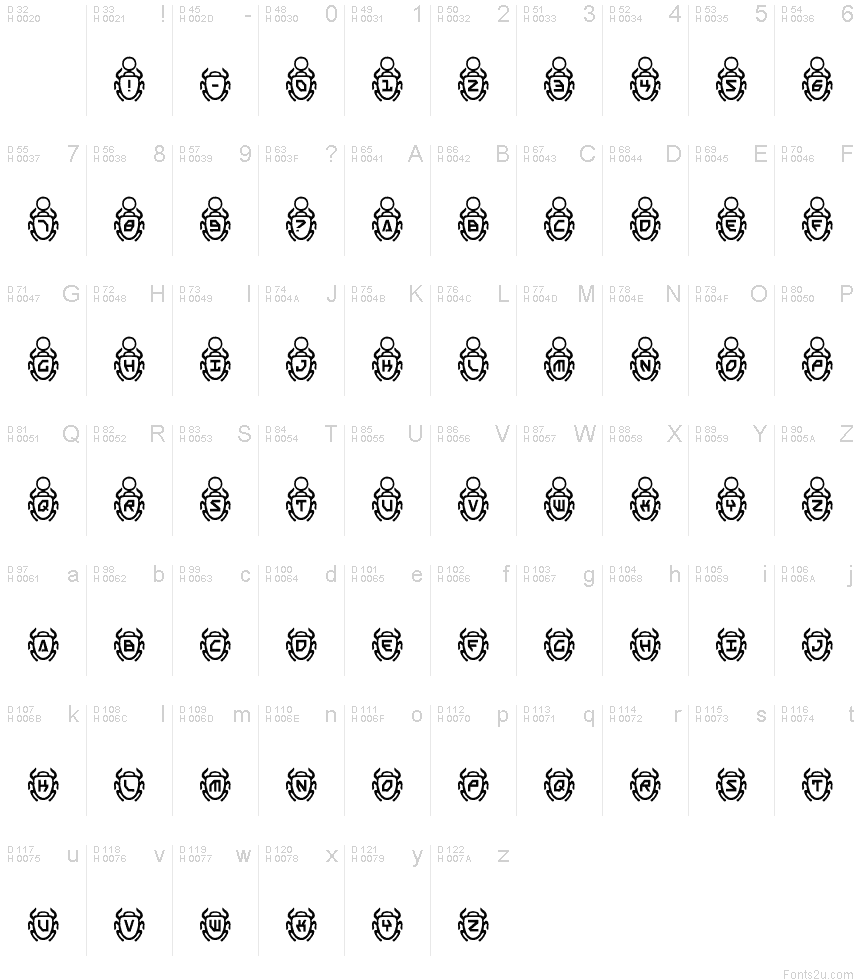
Scarab od Iconian Fonts to darmowy, dekoracyjny krój pisma, który zamienia każdą literę w stylizowany emblemat skarabeusza. Każdy znak jest zamknięty w wyrazistym, obrysowanym pancerzu skarabeusza z geometrycznymi liniami, które sprawiają wrażenie zarówno starożytnych, jak i lekko futurystycznych. Powtarzające się sylwetki owadów tworzą rytmiczny, „tłoczony” wygląd – niemal jak ikony wyryte w kamieniu lub metalu – dzięki czemu Twoje słowa wydają się raczej artefaktami niż tekstem.
Dzięki fontowi Scarab Twoje nagłówki natychmiast zyskują mityczną energię inspirowaną Egiptem, co świetnie sprawdza się w przypadku logotypów gier, plakatów przygodowych, brandingu escape roomów, wydarzeń tematycznych, okładek książek czy wystaw muzealnych. Ten darmowy font najlepiej prezentuje się w dużych rozmiarach, gdzie w pełni docenisz kształt skarabeuszy; w tekście głównym połącz go z prostym, lekkim fontem bezszeryfowym, aby skomplikowane ramki owadów pozostały w centrum uwagi.